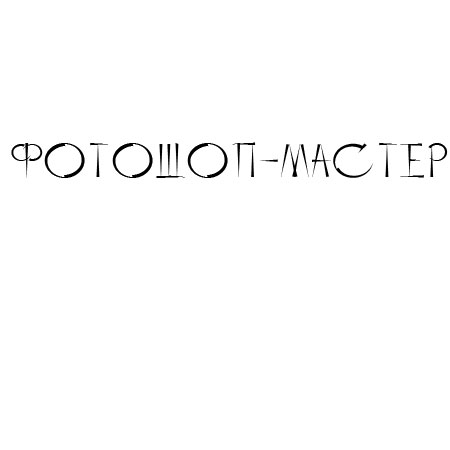
Симпатичный шрифт.
Шрифт БОМБА!
Необычный красивый шрифт
Подходит для Анимэ фоток.
очень красивый
интересный=)
Супер!Давно такой искала)
возьму пожалуй, довольно забавный шрифт :3
О, здорово.